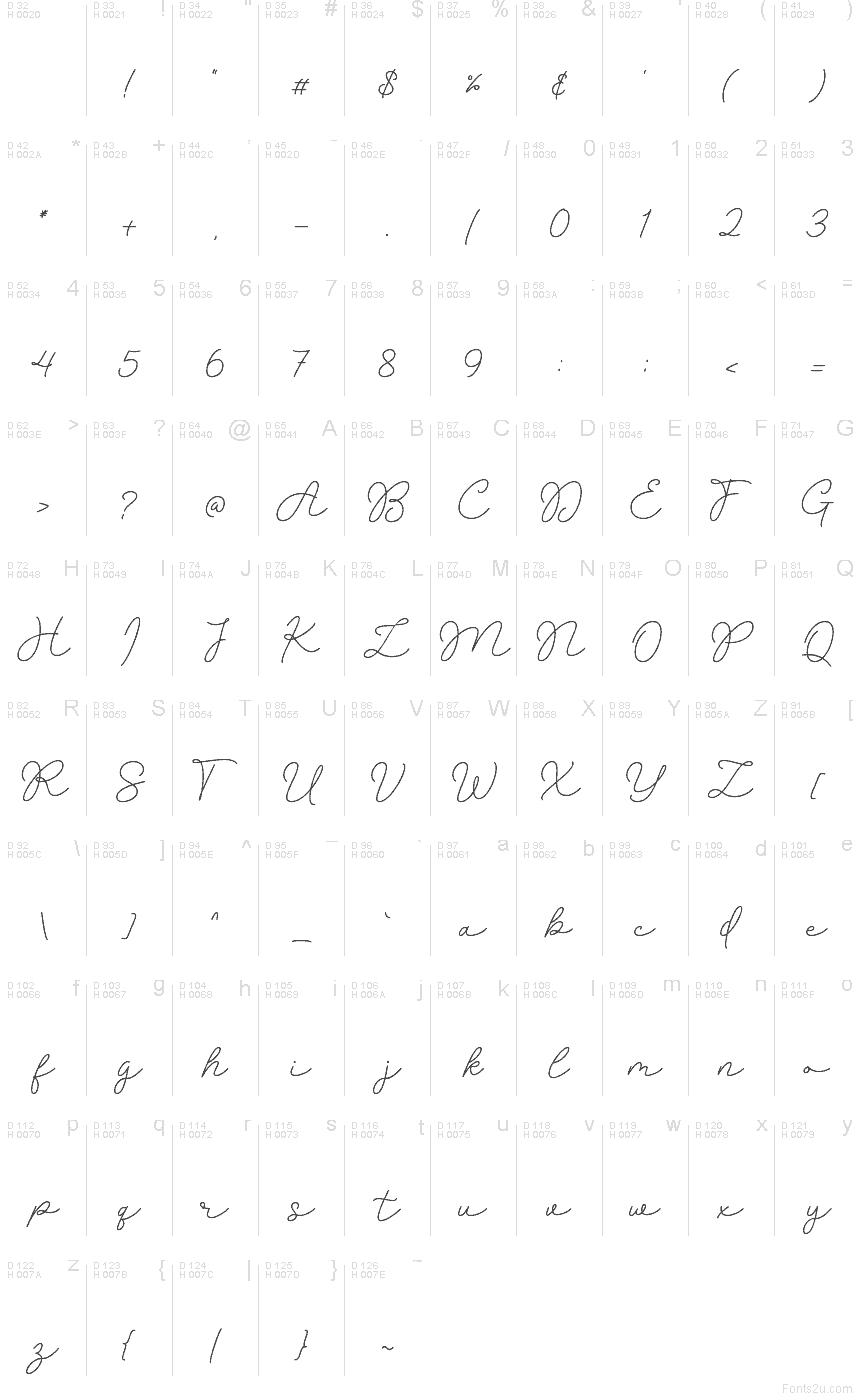
Revision Signature
Revision Signature от MJType — это бесплатный рукописный шрифт с изящным модным акцентом. Буквы словно перетекают одна в другую в едином легком движении, сочетая крупные петли с тонкими, едва соединенными формами. Благодаря этому шрифт выглядит лично, энергично и торжественно, а не просто повседневно.
Он идеально подходит для брендинга бутиков, упаковки косметики, свадебной полиграфии, заголовков в соцсетях, а также обложек книг или альбомов, где название должно выглядеть как авторский росчерк. Будучи бесплатным, этот шрифт отлично работает в логотипах, титульных надписях и монограммах, так как его широкие начальные завитки и эластичные кривые дают коротким словам пространство для «дыхания».